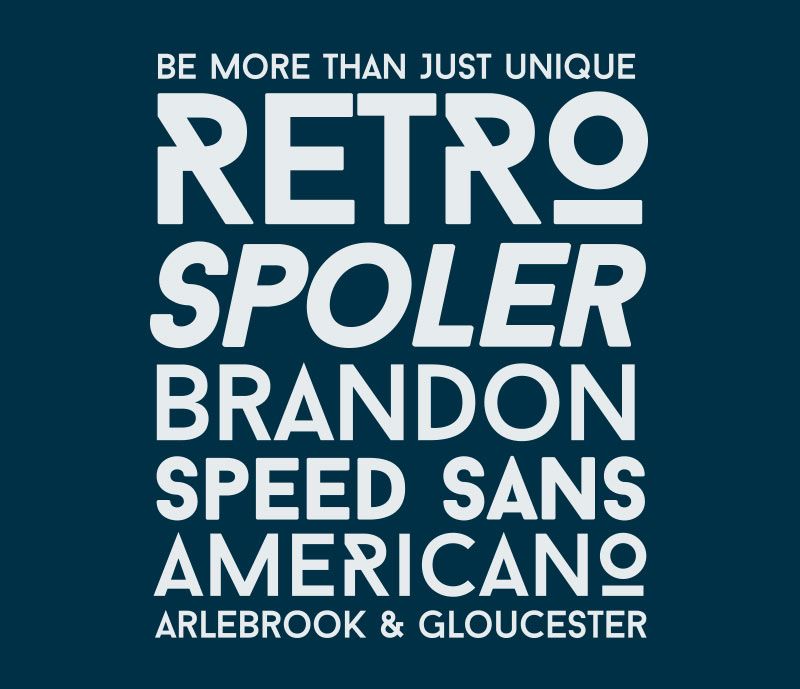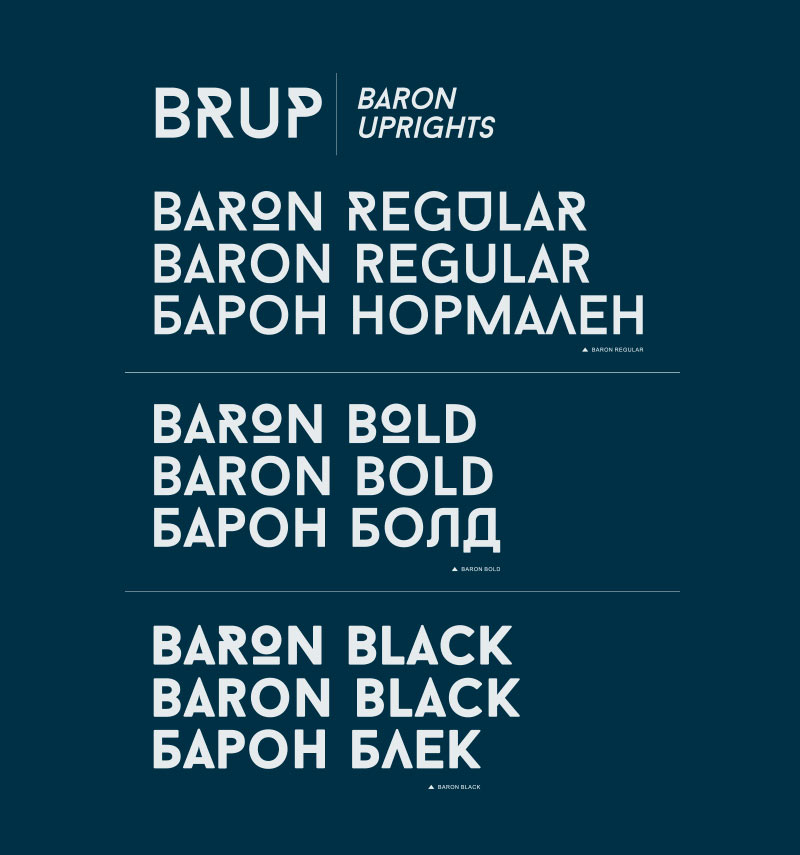
La fuente tipográfica de hoy es Baron, una tipografía libre inspirada en la familia de fuentes clásicas sans serif. Este tipo de letra es ideal para uso en carteles y encabezados. Queremos agradecer desde oldskull a Fontfabric y en especial a su diseñador Frank Hemmekam por ofrecernos esta gran fuente gratuita.